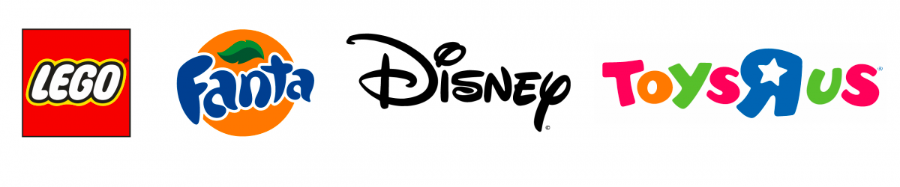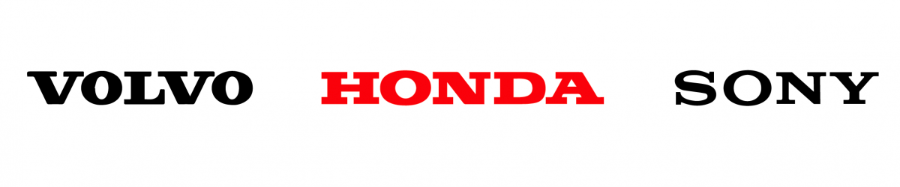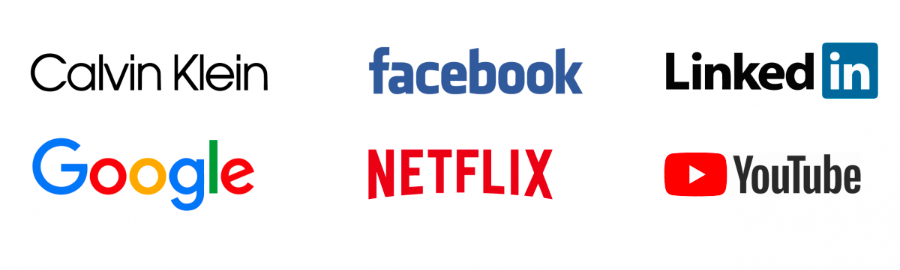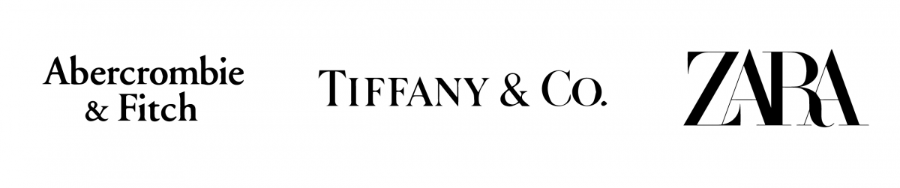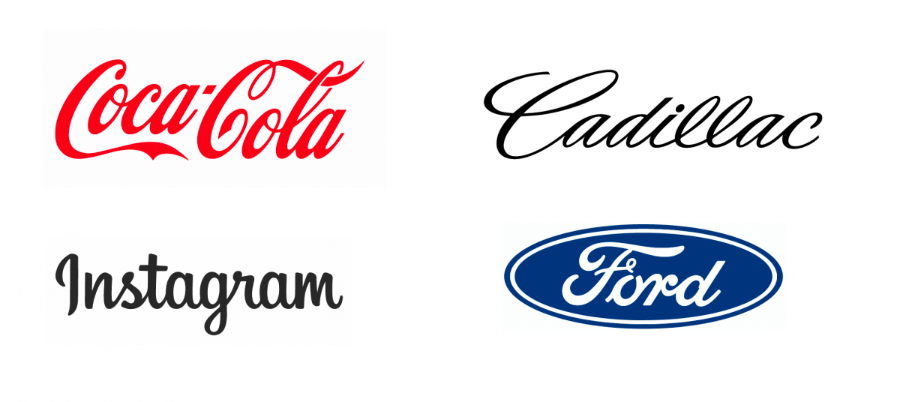
5 kiểu font chữ thường gặp và ảnh hưởng tới tâm lý thị giác trong thiết kế
Font chữ là một trong những yếu tố quan trọng trong thiết kế. Font chữ ảnh hưởng đến người đọc, giúp họ cảm nhận được văn bản, sản phẩm, hay thậm chí là toàn bộ trang web. Do đó, việc lựa chọn font chữ thích hợp sẽ giúp gia tăng sự trải nghiệm của khách hàng hay người sử dụng sản phẩm.
Với con người, hình ảnh không chỉ đơn giản là màu sắc và hình dạng. Những gì mà não bộ con người tiếp nhận còn bao gồm cả chữ cái. Tuy nhiên, từ trước đến nay, so với các hình ảnh, biểu tượng, chữ cái thường được đánh giá là khô khan và khó ghi nhớ hơn xong lại là một phần mà tất cả các thiết kế khi muốn truyền tải nội dung tới khách hàng. Chữ cái được biểu hiện ra sao có tác động rát lớn tới suy nghĩ, cảm xúc và hành vi của con người. Chính vì vậy, không chỉ người làm thiết kế mà các doanh nghiệp cũng cần phải hiểu được tâm lý học thị giác để có thể thuyết phục khách hàng.
Đối với các doanh nghiệp, sự hiểu biết về tâm lý học trong font chữ nói riêng và thiết kế nói chung sẽ quyết định thương hiệu của họ đáng nhớ như thế nào trong tâm trí khách hàng. Khi khách hàng nhìn thấy một ấn phẩm của doanh nghiệp, font chữ có thể gợi lên sự chuyên nghiệp, thân thiện, hiện đại, truyền thống, hoặc bất kỳ tâm trạng nào mà thương hiệu muốn truyền tải. Việc chọn sai font chữ có thể khiến thương hiệu trở nên khó nhớ hoặc gây nhầm lẫn cho khách hàng.
Font chữ có ảnh hưởng tới tâm lý thị giác như thế nào?
Lựa chọn 1 font chữ phù hợp, doanh nghiệp có thể trở thành một phần của nhận thức tiềm thức của khách hàng. Khi họ nhìn thấy hoặc nghe về thương hiệu, họ sẽ tự động nghĩ đến hình ảnh và cảm xúc mà thương hiệu muốn truyền tải. Điều này là mục tiêu cuối cùng của mọi doanh nghiệp: tạo ra một thương hiệu mà khách hàng sẽ luôn nhớ và lựa chọn.
Font chữ là các yếu tố trực quan được sử dụng để truyền thông tin hoặc hiển thị nội dung cho người đọc. Font chữ cũng mang cho mình một thông điệp ẩn để thay đổi cách người đọc cảm nhận về bất kỳ nội dung chính nào đó trong văn bản.
Khi được khai phá tiềm năng, font chữ có thể làm cho một thương hiệu trở nên đáng tin cậy, thân thiện, hoặc truyền cảm hứng hơn - và tác động mạnh mẽ lên tâm lý người tiêu dùng. Ngoài ra, các thiết kế có thể ứng dụng font chữ để định hình phản ứng cảm xúc của cá nhân với một thương hiệu.
5 kiểu font chữ thường gặp trong thiết kế
Có hàng ngàn font chữ được tạo ra nhưng về cơ bản chỉ có 5 kiểu font chữ: Serif, Sans Serif, Slab Serif, Decorative và Scripts. Mỗi kiểu font chữ sẽ có những đặc điểm khác nhau. Hãy cùng Bee Art tìm hiểu về 5 kiểu font chữ này nhé!
1. Font chữ Serif ổn định
Hiểu đơn giản, Serif là các chữ có ít dòng, nét hoặc có chân trên các mẫu chữ. Sự phổ biến của font chữ này đến từ các chân trên các mẫu chữ, nó tạo những nét chữ thanh lịch, mang theo sự truyền thống, trí tuệ, trang trọng
Đây là một kiểu chữ cổ điển và được sử dụng trong các cơ quan hành chính và giới hàm lâm do tính chất trang trọng và vẻ trang nhã của font chữ này mang lại. Một font chữ Serif mà bất kì người Việt Nam nào cũng sử dụng đó chính là font chữ Times New Roman quen thuộc được sử dụng trong tất cả các văn bản của Việt Nam.
Nếu bạn muốn thương hiệu của bạn sở hữu những yếu tố thanh lịch, trang trọng, truyền thống, ổn định, cổ điển thì chắc chắn bạn nên sử dụng font chữ Serif.
Ví dụ một số thương hiệu nổi tiếng sử dụng font chữ Serif trong logo: Wikipedia, TIME, CBS News, Gap, Dior, Rolex, Vogue, Tiffany & Co, ZARA.
Gợi ý một số font chữ Serif đẹp để bạn có thể ứng dụng trong thiết kế: Baskerville, Addington, Garamond, Caslon.
2. Font chữ San Serif thân thiện
Khác với những font chữ Serif với chân chữ cứng cáp, font chữ San Serif gạt bỏ những đường nét không cần thiết. Vì vậy font chữ San Serif thường đại diện cho sự thân thiện, cởi mở. Đó là lý do nhiểu nền tảng mạng xã hội như Youtube, Facebook hay LinkedIn lựa chọn kiểu font chữ này cho logo thương hiệu của họ. Nếu thương hiệu của bạn có tệp khách hàng rộng ví dụ như công ty logistic hay các đơn vị kinh doanh mặt hàng bán lẻ thì chắc chắn bạn nên lựa chọn font chữ Serif cho thiết kế logo của thương hiệu.
font chữ thiết kế 2.png
Ví dụ một số thương hiệu nổi tiếng sử dụng font chữ San Serif trong logo: Nike, Apple, Facebook, Microsoft, Dropbox, Spotify, FedEx, National Geographic
Gợi ý một số font chữ San Serif đẹp để bạn có thể ứng dụng trong thiết kế: Arial, Modelica, Open Sans.
3. Font chữ Slab Serif mạnh mẽ
Font chữ Serif dạng Slab là một dạng chữ táo báo và đậm hơn so với font Serif thông thường. Đây là một font chữ quyết đoán mạnh mẽ, phù hợp với các doanh nghiệp thực tế và đáng tin cậy. Nó thường dày hơn ở các phần đường viền, font Slab Serif thừa hưởng sự ổn định và truyền thống của Serif, nhưng cũng táo bạo và độc đáo hơn.
Font Slab Serif thường có cảm giác nam tính và xù xì hơn. Các công ty xe hơi và điện tử có thể sử dụng nó để truyền đạt cảm giác nam tính, mạnh mẽ trong thương hiệu của họ.